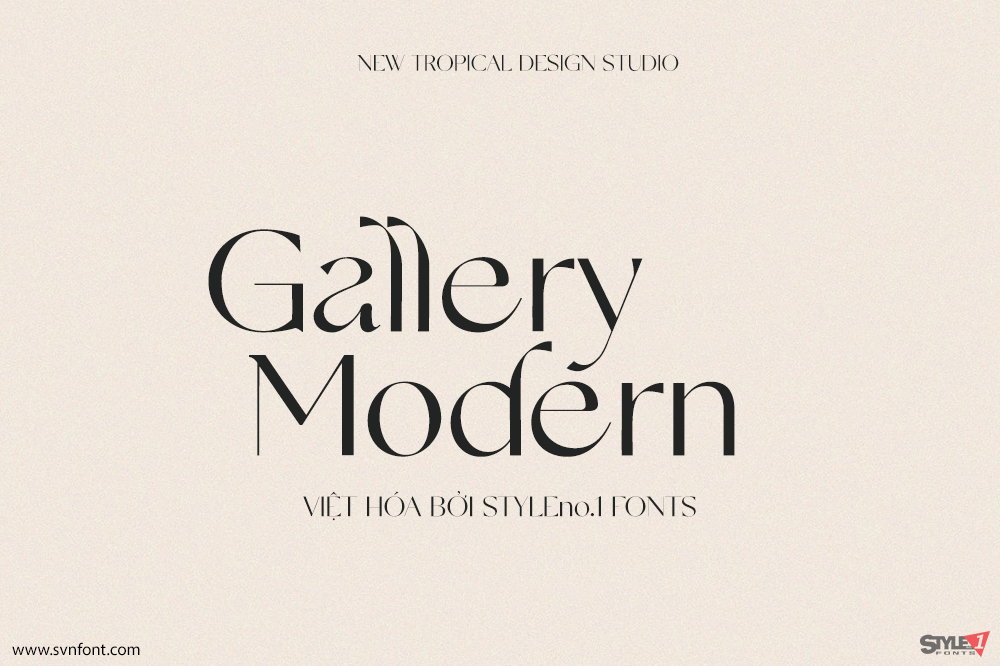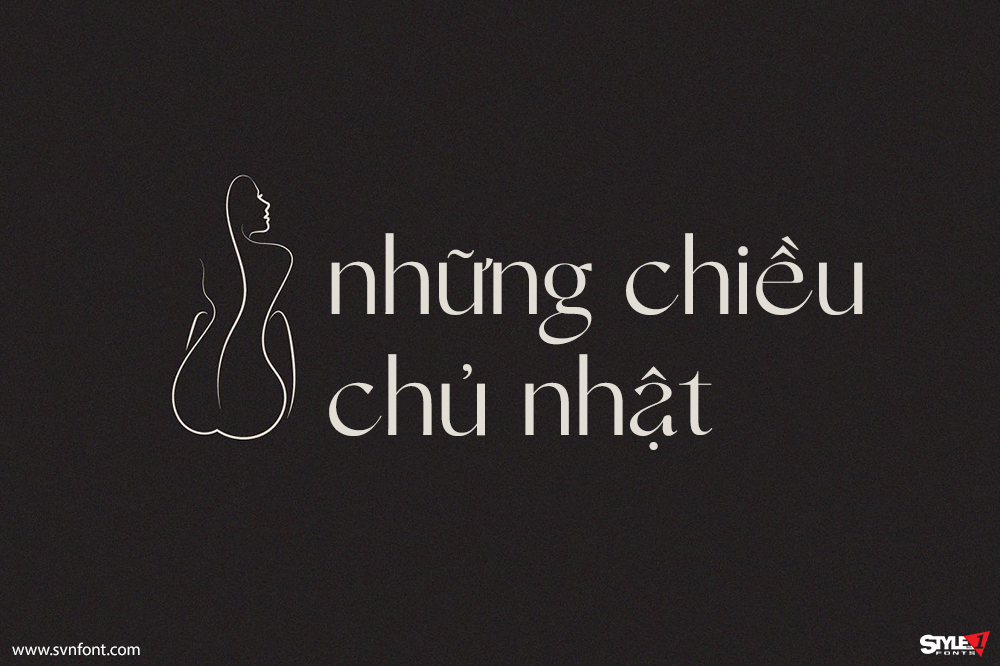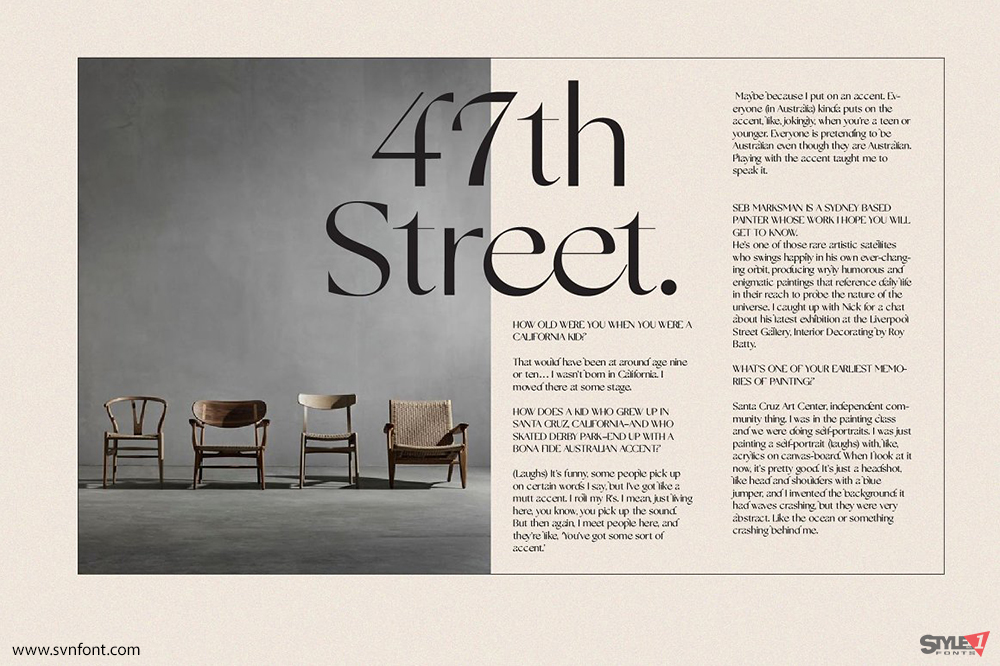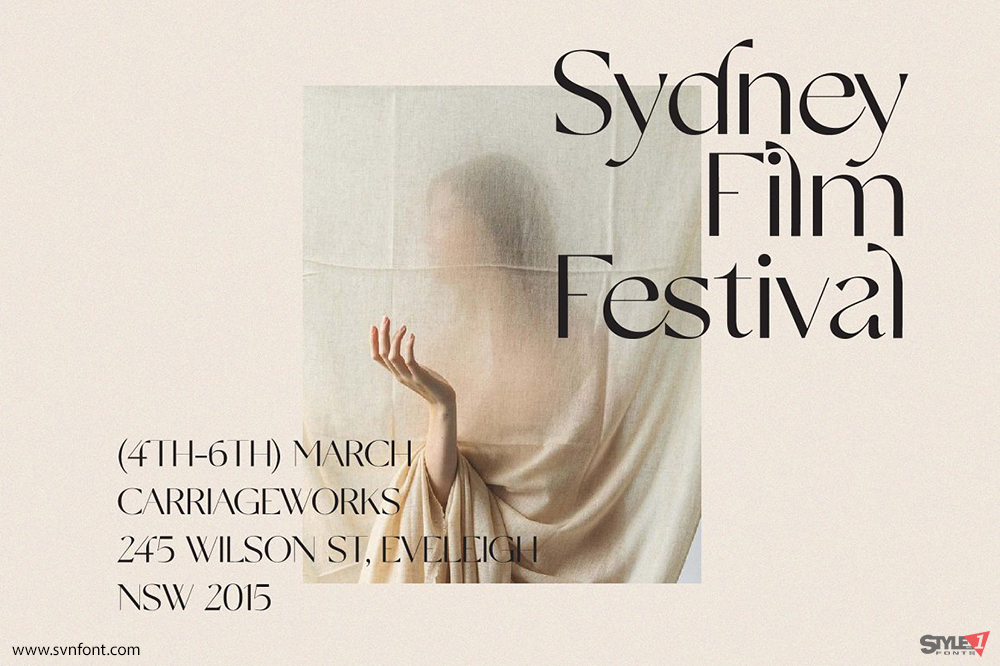
Tải Font SVN-Gallery Moder đẹp dành cho thiết kế
Gallery Modern là một kiểu font serif cao cấp với thiết kế thanh lịch, hiện đại nhưng vẫn giữ được nét cổ điển trong từng đường nét. Font này thường được ứng dụng trong các thiết kế cao cấp như tạp chí thời trang, logo thương hiệu hoặc các ấn phẩm truyền thông mang tính nghệ thuật.
Đặc điểm nổi bật của Font Gallery Modern
• Serif tinh tế: Các chân chữ được xử lý sắc sảo, thanh mảnh và có độ cong mềm mại, tạo nên vẻ thanh lịch và chuyên nghiệp.
• Độ tương phản cao: Font có sự chênh lệch rõ rệt giữa nét thanh – nét đậm, giúp nổi bật tiêu đề và tạo điểm nhấn thị giác mạnh mẽ.
• Tỉ lệ hình học cân đối: Các ký tự được thiết kế cân đối và có khoảng cách hợp lý, mang lại cảm giác hài hòa và dễ đọc.
• Phong cách sang trọng: Gallery Modern kết hợp giữa vẻ đẹp cổ điển và nét hiện đại, rất phù hợp với các thiết kế mang tính thời trang, cao cấp.
Ứng dụng của Font Gallery Modern
• Tạp chí thời trang, lookbook, editorial design: Font giúp tạo sự sang trọng và nổi bật cho tiêu đề hoặc nội dung chính.
• Thiết kế logo, bộ nhận diện thương hiệu: Phù hợp với các thương hiệu thời trang, mỹ phẩm, nội thất cao cấp.
• Poster, thiệp mời, danh thiếp: Tạo ấn tượng chuyên nghiệp và thanh lịch ngay từ cái nhìn đầu tiên.
• Website phong cách tối giản và hiện đại: Font có thể kết hợp với nền trắng hoặc hình ảnh thời trang để tạo cảm giác tinh tế.
• Ấn phẩm nghệ thuật, triển lãm, catalogue sản phẩm: Mang lại vẻ đẹp cổ điển pha trộn hiện đại, giúp sản phẩm trở nên nổi bật và có chiều sâu.
Font Gallery Modern không chỉ là một kiểu chữ, mà là một biểu tượng của sự thanh lịch và đẳng cấp. Với thiết kế chỉn chu, hiện đại và dễ ứng dụng, nó trở thành sự lựa chọn hàng đầu cho các designer khi muốn thể hiện phong cách sang trọng và chuyên nghiệp trong các ấn phẩm thiết kế.